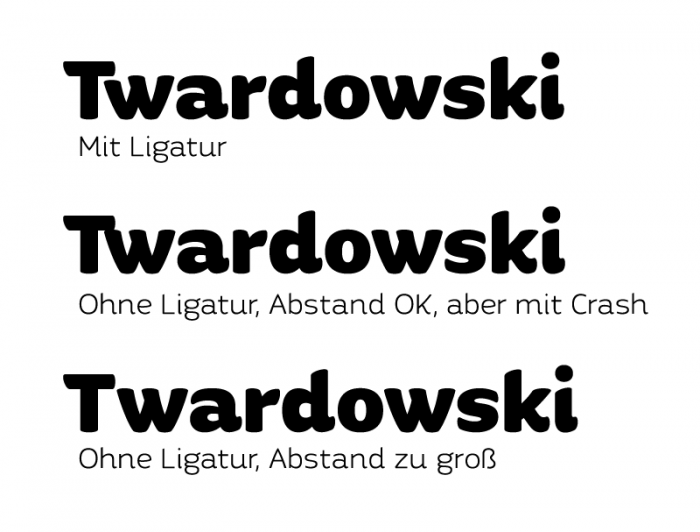
Unerwünschte Ligaturen
ich hab kürzlich einen Schriftentwurf bei MyFonts eingereicht, um die Schrift dort zu veröffentlichen. Gestern kam die Antwort: Ja, sie wären ganz angetan von meiner Schrift, ich solle aber zunächst einige Dinge an der Schrift überarbeiten. Unter anderem haben ihnen bestimmte Ligaturen nicht gefallen:
"For letter combinations like “Tv” or “Tw”, the two letters should only be kerned to one another, not replaced by a special ligature."
Soweit zwar richtig, aber in meinem fettesten Schriftgrad stößt der horizontale Balken vom T mit dem v/w zusammen (siehe Bild) – daher hatte ich dafür eben Ligaturen angelegt. Ich weiß jetzt nicht, was zu tun ist... wenn diese Ligaturen aus der Schrift entfernt werden und das ganze nur per Kerning gelöst wird, ergibt sich eine zu große Lücke an dieser Stelle.
Wie würdet ihr es lösen?
Ich bin nur Anwender und habe von der (technischen) Gestaltung (bzw. Programmierung) kaum Ahnung … aber für mich klingt das hier eher nach Contextual Alternates, sprich ein „w“ weiß, dass es seinen Arm ein Stück einziehen muss, wenn ein „T“ neben ihm steht.
Die Schrift und die Idee für das Tw-Problem finde ich übrigens fein!
Aber den oberen und unteren Bogen im „s“ im vergleich zum mittleren deutlich zu mager.